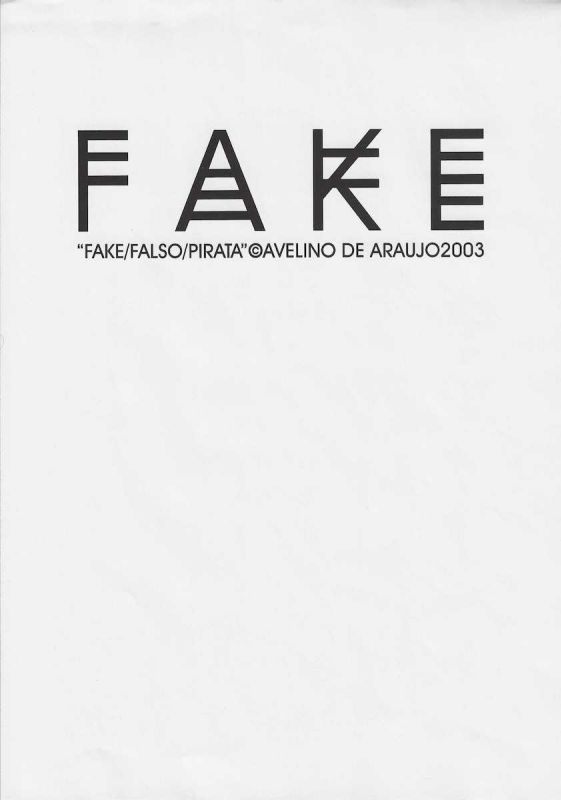
Fake Falso Pirata é uma impressão gráfica de Avelino de Araújo realizada em 2003, vinculada à poesia visual, à poesia experimental, à arte conceitual, à tipografia e às investigações intersígnicas associadas ao campo do Poema Processo.
Avelino de Araújo
Data: 2003
Dimensões: 29,7 x 21,2 cm
Fake Falso Pirata é uma impressão gráfica de Avelino de Araújo realizada em 2003, vinculada à poesia visual, à poesia experimental, à arte conceitual, à tipografia e às investigações intersígnicas associadas ao campo do Poema Processo. A composição apresenta a palavra inglesa FAKE, correspondente a falso, simulacro, imitação ou objeto não autêntico, construída com quatro letras maiúsculas negras de grandes dimensões. Cada caractere recebe alterações internas que perturbam a escrita convencional. As letras F e E apresentam várias barras horizontais, a letra A contém linhas transversais repetidas e a letra K é atravessada por hastes que produzem sobreposição, cruzamento e ambiguidade visual. Essas interferências fazem com que a palavra permaneça reconhecível, mas pareça adulterada, duplicada, falsificada ou submetida a uma reprodução defeituosa. A forma tipográfica participa diretamente do significado da obra, pois o termo que designa falsidade é apresentado por meio de letras que simulam, repetem e deformam suas próprias estruturas. A inscrição inferior identifica a obra como FAKE FALSO PIRATA, aproximando três ideias relacionadas, mas não idênticas. Fake indica algo fabricado para parecer verdadeiro. Falso questiona autenticidade, origem e correspondência com o real. Pirata remete à reprodução, circulação ou apropriação realizada sem autorização. A sequência permite interpretar a obra como reflexão crítica sobre cópia, falsificação, autoria, originalidade, reprodução técnica, propriedade intelectual, circulação de imagens e valor cultural. Realizada em 2003, a peça também dialoga com o crescimento da reprodução digital, do compartilhamento de arquivos e da multiplicação acelerada de conteúdos no início do século vinte e um. Avelino de Araújo transforma a palavra em imagem e utiliza a alteração gráfica das letras para problematizar a confiança depositada na escrita e nos sistemas de identificação. O amplo espaço branco ao redor concentra a atenção na palavra e reforça sua aparência de título, marca, aviso, classificação ou selo de autenticidade invertido. A obra integra a produção do artista baseada na apropriação de vocábulos, alfabetos, códigos gráficos e ambiguidades linguísticas para construir poemas visuais de leitura direta e reflexão conceitual. Palavras chave para indexação: Avelino de Araújo, Fake Falso Pirata, Fake, Falso, Pirata, 2003, impressão gráfica, poesia visual brasileira, poema visual, poesia experimental, arte conceitual, Poema Processo, falsificação, cópia, pirataria, reprodução, autenticidade, originalidade, autoria, propriedade intelectual, cultura digital, tipografia experimental, palavra imagem, deformação tipográfica, linguagem visual, semiótica, intersigno, comunicação visual, arte gráfica brasileira, múltiplo gráfico, arquivo de poesia visual, arte brasileira do século vinte e um.Fake False Pirate is a graphic print by Avelino de Araújo produced in 2003 and associated with visual poetry, experimental poetry, conceptual art, typography and intersemiotic investigations connected with the field of the Poema Processo movement. The composition presents the English word FAKE, referring to something false, simulated, imitated or inauthentic, constructed with four large black capital letters. Each character contains internal alterations that disturb conventional writing. The letters F and E present several horizontal bars, the letter A contains repeated crossbars and the letter K is crossed by strokes that create superimposition, intersection and visual ambiguity. These interventions allow the word to remain recognizable while making it appear altered, duplicated, falsified or affected by defective reproduction. Typographic form participates directly in the meaning of the work because the term used to identify falsity is presented through letters that simulate, repeat and deform their own structures. The lower inscription identifies the work as FAKE FALSO PIRATA, bringing together three related but distinct ideas. Fake indicates something manufactured to resemble an authentic object. Falso, the Portuguese word for false, questions authenticity, origin and correspondence with reality. Pirata, the Portuguese word for pirate, refers to reproduction, circulation or appropriation performed without authorization. The sequence allows the work to be interpreted as a critical reflection on copying, forgery, authorship, originality, technical reproduction, intellectual property, circulation of images and cultural value. Produced in 2003, the piece also relates to the expansion of digital reproduction, file sharing and the accelerated multiplication of content at the beginning of the twenty first century. Avelino de Araújo transforms the word into image and uses graphic alteration of letters to question the trust placed in writing and systems of identification. The broad white space surrounding the composition focuses attention on the word and reinforces its appearance as a title, brand, warning, classification or inverted seal of authenticity. The work belongs to the production of Avelino de Araújo based on the appropriation of words, alphabets, graphic codes and linguistic ambiguities to construct visual poems with immediate recognition and conceptual depth. Keywords for indexing: Avelino de Araújo, Fake Falso Pirata, Fake, False, Pirate, 2003, graphic print, Brazilian visual poetry, visual poem, experimental poetry, conceptual art, Poema Processo, forgery, copy, piracy, reproduction, authenticity, originality, authorship, intellectual property, digital culture, experimental typography, word image, typographic deformation, visual language, semiotics, intersign, visual communication, Brazilian graphic art, graphic multiple, visual poetry archive, twenty first century Brazilian art.
Impressão gráfica em tinta preta sobre papel claro, composta pela palavra FAKE em caracteres maiúsculos de grande formato, posicionada na região superior da folha. As letras apresentam desenho geométrico, espessura regular e modificações internas produzidas por barras horizontais e diagonais. A letra F possui barras repetidas, a letra A contém três linhas horizontais internas, a letra K apresenta hastes sobrepostas que dificultam a percepção imediata de sua estrutura e a letra E possui diversas barras paralelas. As alterações criam ritmo, repetição e aparência de código visual. Abaixo da palavra encontra se a inscrição FAKE FALSO PIRATA, seguida pelo símbolo de autoria, pelo nome Avelino de Araújo e pelo ano 2003. A maior parte do suporte permanece sem impressão, produzindo forte contraste entre a concentração tipográfica e o campo branco. A folha apresenta leves ondulações, vincos, marcas de dobra e discretos sinais de manuseio. A peça pode ser classificada como poema visual, impressão de artista, múltiplo gráfico, estudo tipográfico e documento conceitual, sendo relevante para pesquisas sobre Avelino de Araújo, Poema Processo, poesia visual, falsificação, pirataria, autoria, reprodução técnica, linguagem, tipografia, semiótica e produção gráfica brasileira.OBSERVATION TEXT IN ENGLISH: Graphic print in black ink on light colored paper composed of the word FAKE in large capital characters positioned in the upper region of the sheet. The letters have a geometric design, regular thickness and internal modifications produced by horizontal and diagonal bars. The letter F has repeated bars, the letter A contains three internal horizontal lines, the letter K presents overlapping strokes that complicate the immediate perception of its structure and the letter E contains several parallel bars. These alterations create rhythm, repetition and the appearance of a visual code. Below the word appears the inscription FAKE FALSO PIRATA, followed by the authorship symbol, the name Avelino de Araújo and the year 2003. Most of the support remains unprinted, producing strong contrast between typographic concentration and the white field. The sheet presents slight undulations, creases, fold marks and minor traces of handling. The piece may be classified as a visual poem, artist print, graphic multiple, typographic study and conceptual document, making it relevant to research on Avelino de Araújo, Poema Processo, visual poetry, forgery, piracy, authorship, technical reproduction, language, typography, semiotics and Brazilian graphic production.
Fake False Pirate is a graphic print by Avelino de Araújo produced in 2003 and associated with visual poetry, experimental poetry, conceptual art, typography and intersemiotic investigations connected with the field of the Poema Processo movement.